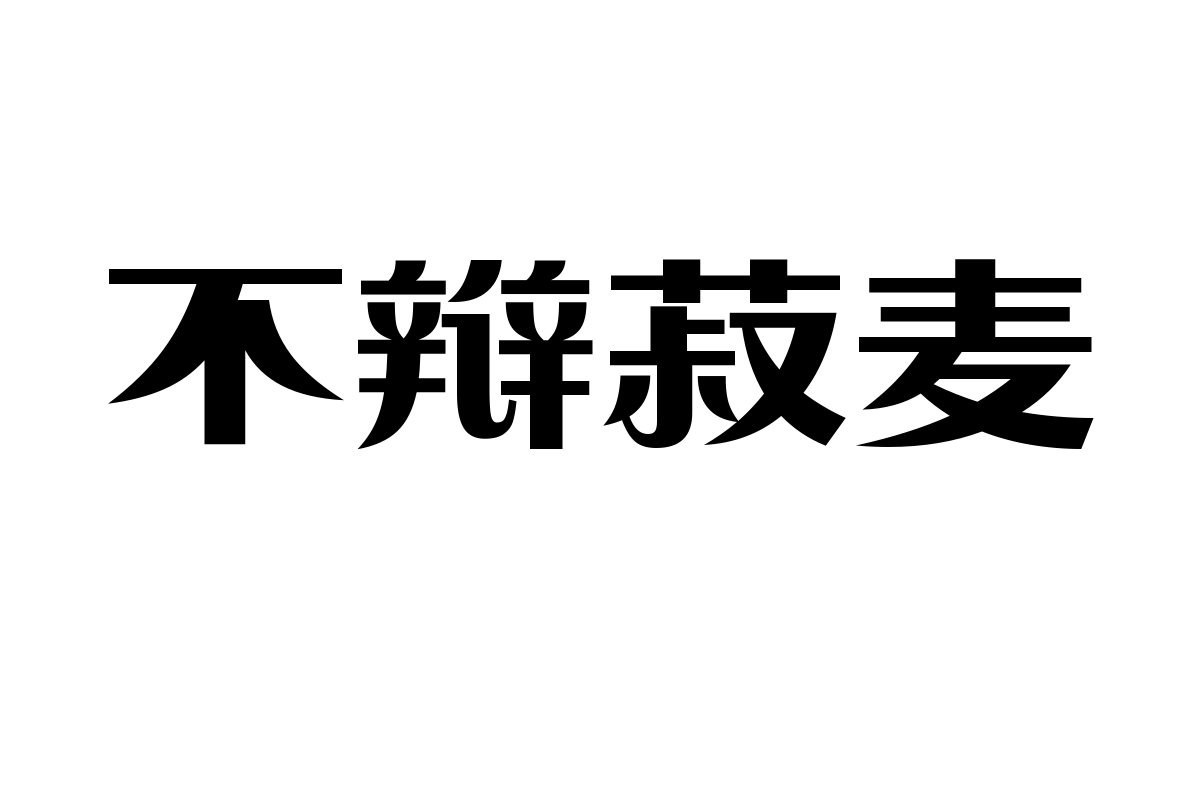
仓耳秀蓁体是一种新型的汉字字体,由仓耳秀蓁文化传媒有限公司设计。这种字体具有独特的风格和特点,适合用于各种场景,如广告、包装、书籍等。
仓耳秀蓁体的字形结构紧凑,笔画流畅,具有较强的视觉冲击力。它的笔画粗细适中,既有力度又不失柔美,给人一种优雅而有力的感觉。同时,这种字体还具有一定的装饰性,使得整个文字更加生动有趣。
仓耳秀蓁体在设计上注重细节,每个字都经过精心打磨,力求达到完美的效果。无论是字形的大小、间距还是行距,都经过精心设计,使得整个文字布局更加和谐统一。
总的来说,仓耳秀蓁体是一种非常独特且具有吸引力的汉字字体,适合用于需要强调视觉效果的场景。